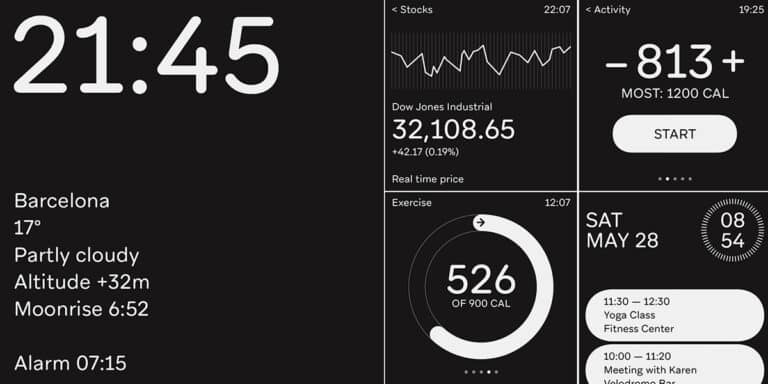
Aribau Rounded: Freundliches Arbeitstier
Bei Emtype, der Foundry von Eduardo Manso aus Barcelona, erschien jetzt eine Erweiterung der Schriftfamilie Aribau.
Die Neue heißt Aribau Rounded und ist das freundliche Gegenstück zur Aribau Grotesk. Ursprünglich als Customfont für eine Bank entstanden, behält die gerundete Variante die Klarheit der Aribau Grotesk bei, fügt aber einen Hauch von Wärme hinzu.
Ihre abgerundeten Formen sind einladend und sympathisch, aber nicht übertrieben verspielt. Sie eignet sich  für eine Vielzahl von Anwendungen, von Geschäftsberichten übers Branding bis zum Interfacedesign. Die Familie umfasst 16 Schnitte, acht Stärken von Thin bis Black plus Italics. Die komplette Familie plus den Variable Font gibt es bei Emtype momentan für 189 statt 299 Euro, Einzelschnitte kosten jetzt 30 statt 45 Euro.
Acht Stärken plus Kursive macht insgesamt 16 Schnitte. Und einen Variable Font gibt es auch.
Aribau Rounded und Aribau Grotesk.
Rounded und Grotesk haben die gleiche Struktur.